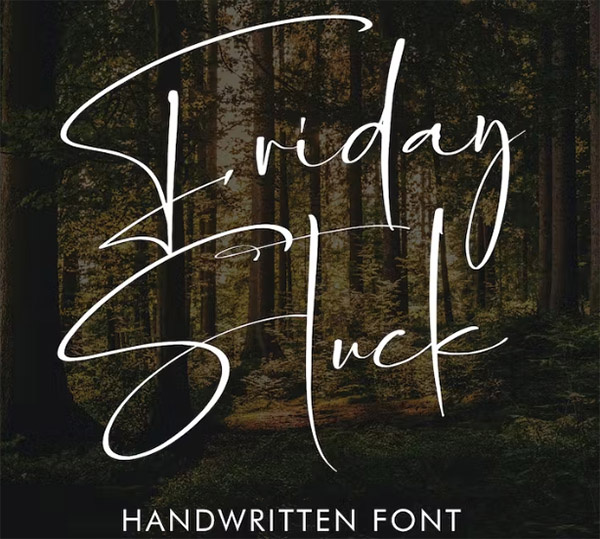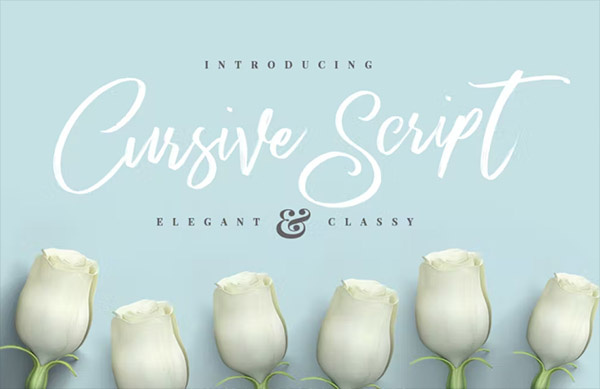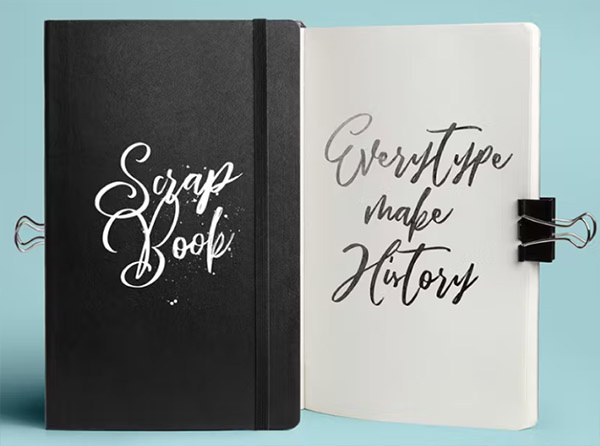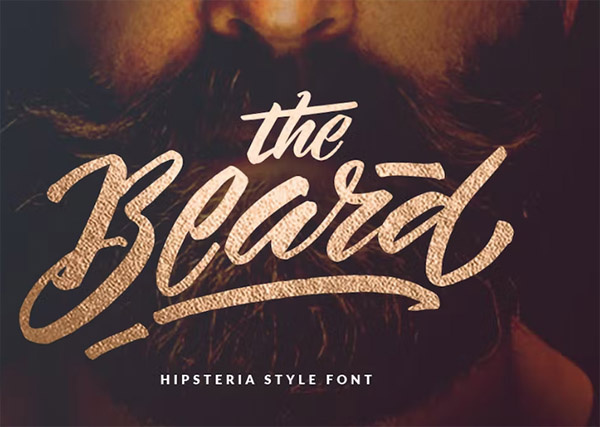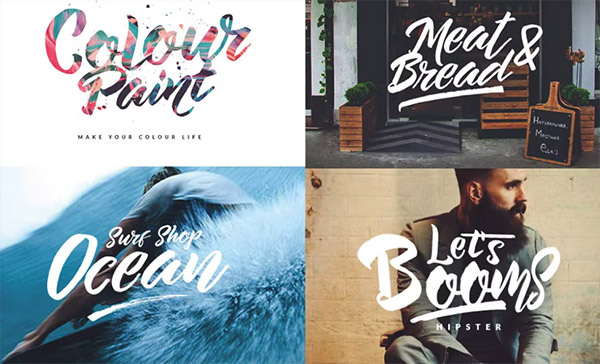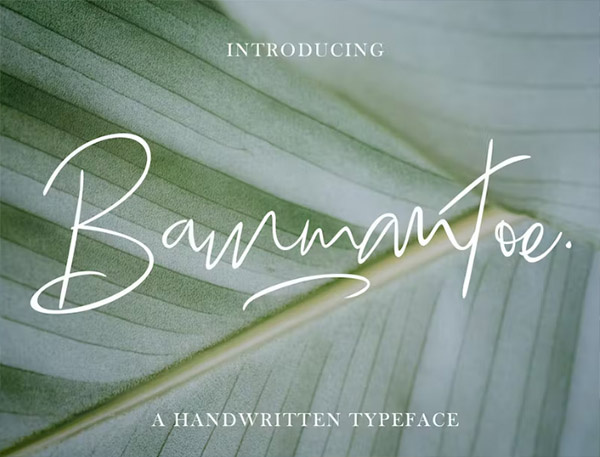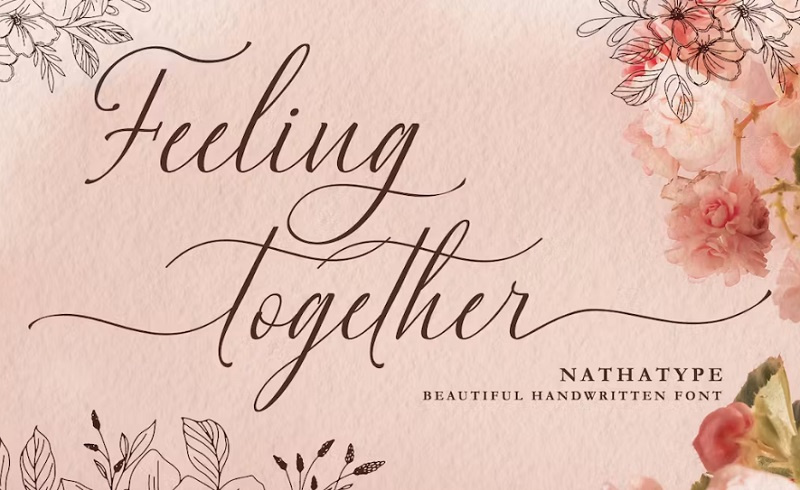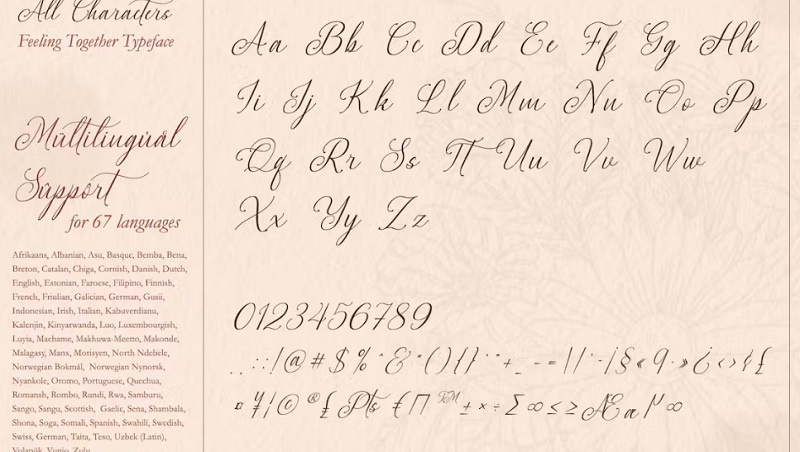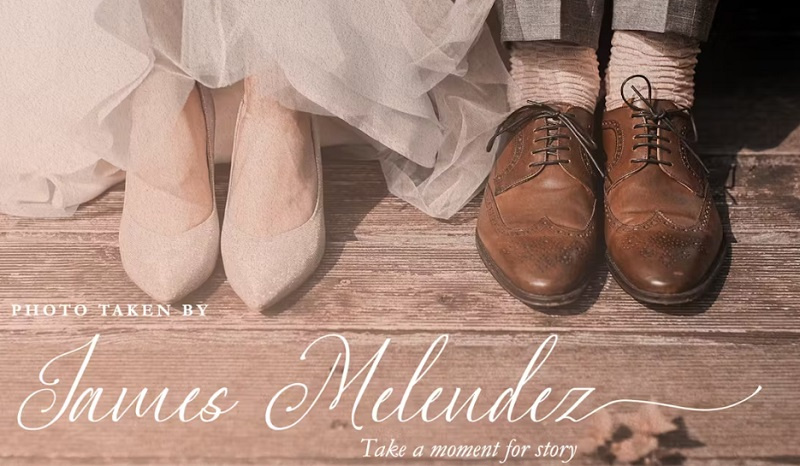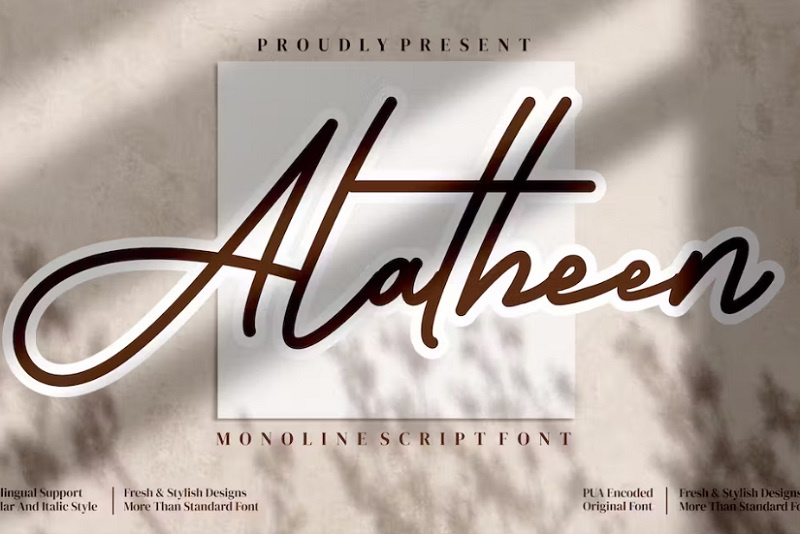
فونت انگلیسی چسبیده از جی اف ایکس دانلود. در این مجموعه شاهد 6 فونت جذاب با نام های فونت انگلیسی چسبیده Friday Stuck، فونت سرهم انگلیسی Cursive Brush، فونت انگلیسی The Beard و فونت دستخط سرهم Bammantoe می باشد. با سبک جدید و متفاوت از سایت gfx با لینک مستقیم. این مجموعه فونت انگلیسی بهم چسبیده برای بسیاری از پروژه های مختلف مانند نقل قول، لوگو، سربرگ وبلاگ، پوستر، نواربندی، مد، پوشاک، نامه، دعوت نامه، لوازم التحریر و غیره مناسب است.
مجموعه فونت های انگلیسی چسبیده
1- دانلود 5 فونت انگلیسی چسبیده و سرهم
این مجموعه بهترین فونت های چسبیده و دستخط انگلیسی ایده آل برای آرم ها، نقل قول های دست نویس، بسته بندی محصول، سربرگ، پوستر، کالا، رسانه های اجتماعی و کارت های تبریک و غیره می باشد.
2- دانلود فونت انگلیسی بهم چسبیده Feeling Together
این فونت انگلیسی چسبیده به سبک دستخط و خوشنویسی می باشد که برای فونت های رمانتیک و عاشقانه، فونت های دستخطی و ... بسیار مناسب است. همچنین این فونت انگلیسی بهم چسبیده برای برای طراحی و ادیت عکس نیز مناسب می باشد.
3- فونت انگلیسی چسبیده زیبا
Alatheen نام این فونت انگلیسی چسبیده زیبا است که مناسب برای هر پروژه ای می باشد. یکی از بهترین فونت ها برای طراحی و ادیت عکس می باشد که حس زیبایی و لوکس بودن را به طراحی های شما خواهد داد. این فونت خط چسبیده انگلیسی شامل فایل های OTF/TTF/WOFF می باشد.
✅ نام فونت انگلیسی1: Friday Stuck
✅ نام فونت انگلیسی2: Cursive Brush
✅ نام فونت انگلیسی3: The Beard
✅ نام فونت انگلیسی4: Bammantoe
✅ نام فونت انگلیسی5: Feeling Together
✅ نام فونت انگلیسی6: Alatheen
✅ مجموعه ای از حروف بزرگ و کوچک ، عدد، نماد و نشانه گذاری